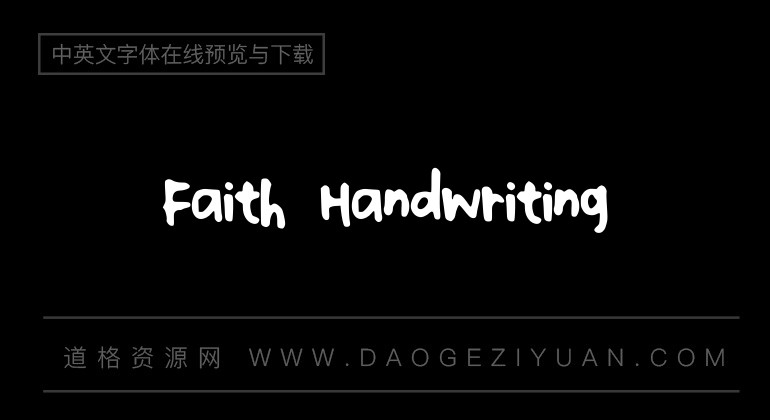
Faith Handwriting
Faith Handwriting 字体是一种基于手写字体的字体风格,非常适合用于卡片、信件、海报、广告等场合。它的字母形状呈现出自然、流畅、轻松的感觉,有着良好的可读性。这种字体的特点是每个字母间距离较大,字母形状有些不规则,呈现出手写的效果,非常适合用于需要显示个性、亲切感和温暖感的场合。Faith Handwriting 字体可以通过许多字体网站免费下载,是许多设计师、教师、学生和创意人士的首选字体之一。
Faith Handwriting是一款非常不错的手写艺术字体,具有很好的视觉感,适合于文化类的宣传设计、商业类品牌的广告和产品包装设计以及个性化文字排版等较多场景。